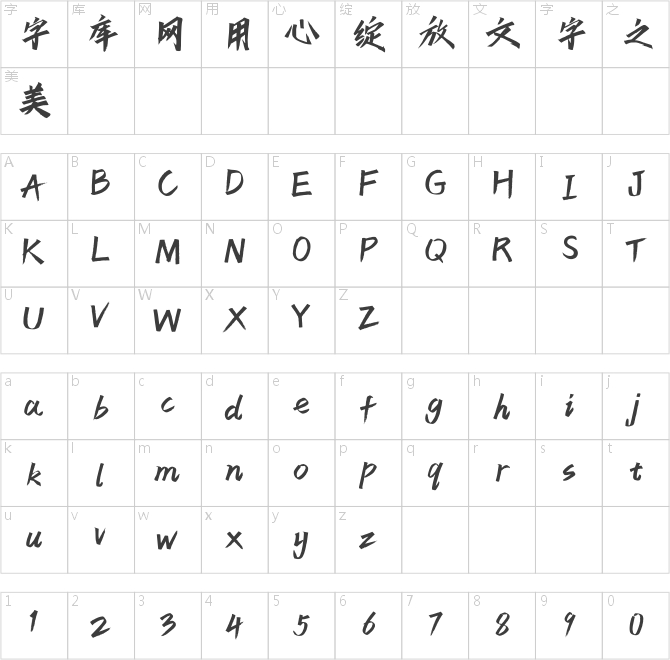
點(diǎn)字瀟灑體 詳情頁(yè)
字體名稱: 點(diǎn)字瀟灑體
點(diǎn)字瀟灑體字體字庫(kù)是一款讓人賞心悅目、百看不厭的中文字體,適合各類廣告和產(chǎn)品包裝設(shè)計(jì)應(yīng)用,字體大小1.12MB,格式為ttf字體,上傳用戶是rose,作者/版權(quán)方為點(diǎn)字